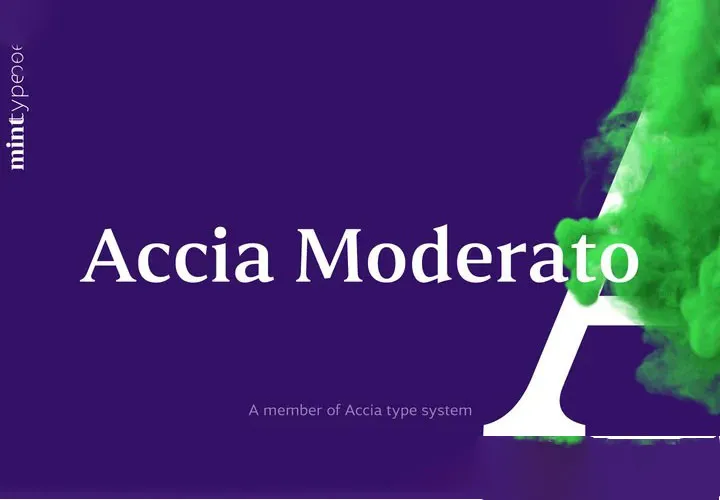
A Accia Moderato é uma elegante fonte Serif projetada por Mint Type. Com sua contrastes moderados e x-height grande, ela se destaca como uma escolha incrível para o corpo principal do texto. Suas linhas sóbrias e harmoniosas garantem um texto profissional e sofisticado que complementará perfeitamente qualquer layout digital ou impresso. Este é o tipo de fonte que torna seu trabalho não apenas visualmente atraente, mas também de alta qualidade, fazendo-o uma escolha ideal para qualquer projeto gráfico que precise de um touch elegante. Não importa se você está trabalhando em designs profissionais ou sites web, a Accia Moderato estará sempre pronta para ajudá-lo a criar conteúdo agradável aos olhos do seu público-alvo.